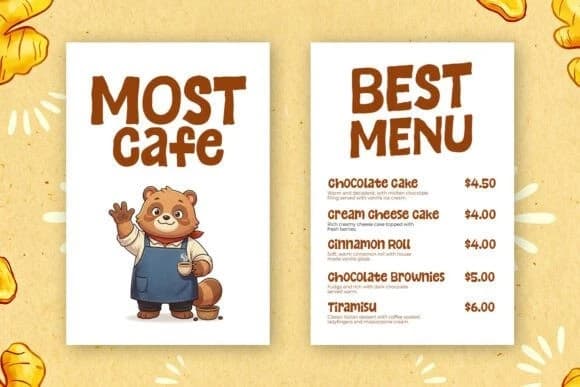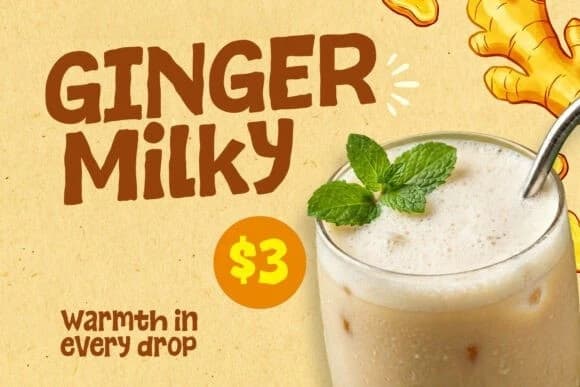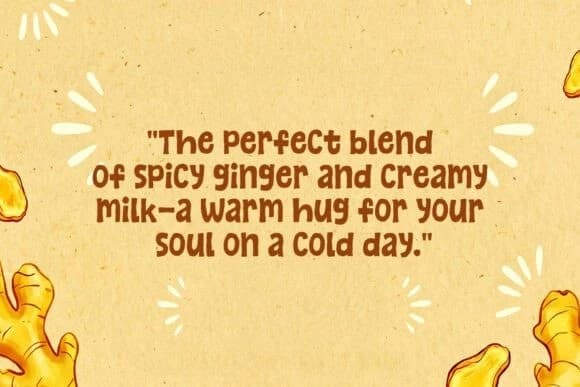
Ginger Times Yazı Tipi
Ginger Times Font, posterler, logolar, dergiler, kitap kapakları, afişler ve çok daha fazlası için mükemmel, modern ve sevimli bir gösterim yazı tipidir! Bu harika yazı tipini edinin ve onu kullanarak hoş tasarımlar oluşturun. Oldukça geniş bir proje yelpazesine kolayca uyum sağlar.
Ginger Times Font, posterler, logolar, dergiler, kapaklar, afişler ve çok daha fazlası için mükemmel, modern ve sevimli bir gösterim yazı tipidir! Bu harika fontu edinin ve onu güzel tasarımlar oluşturmak için kullanın. Oldukça geniş bir proje yelpazesine kolayca uyum sağlar.